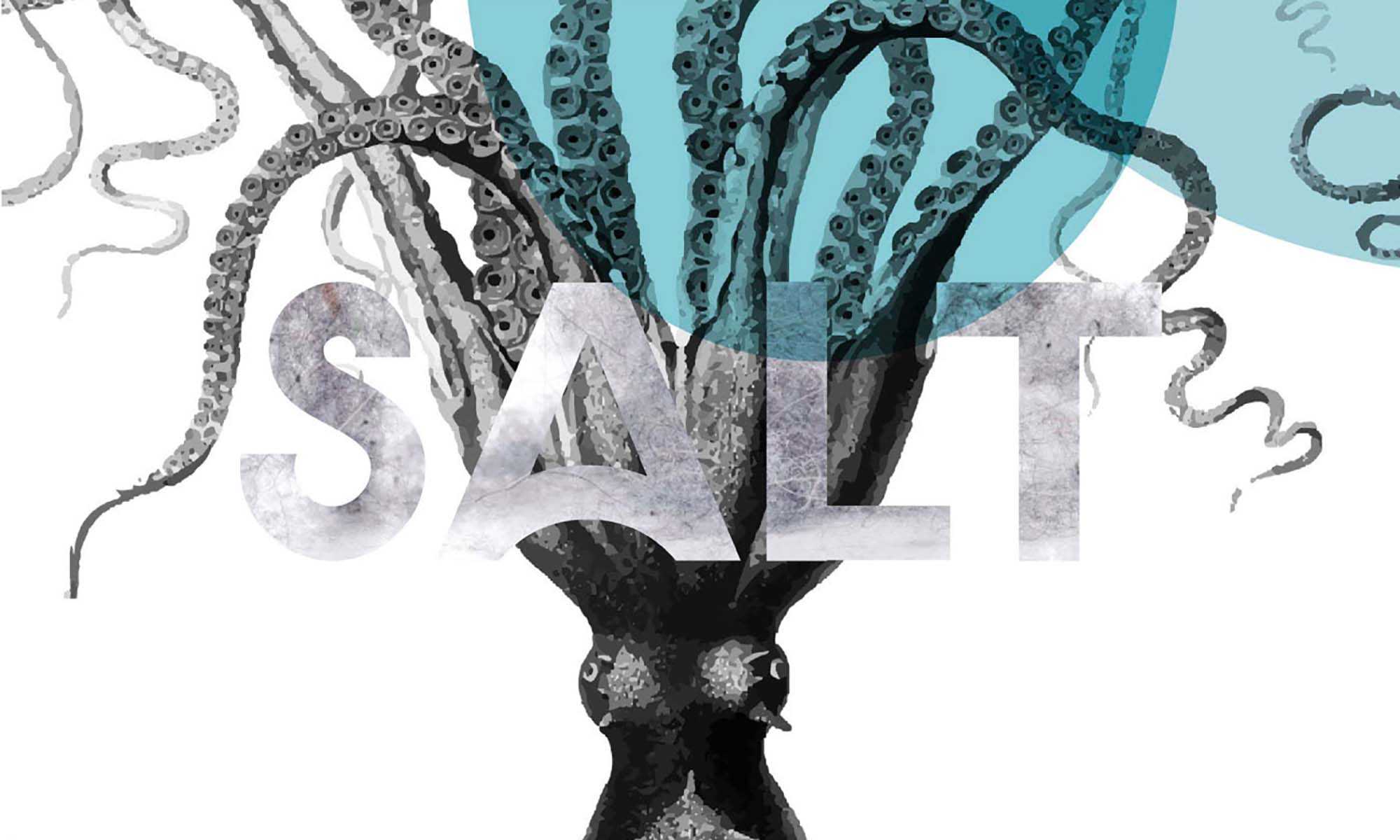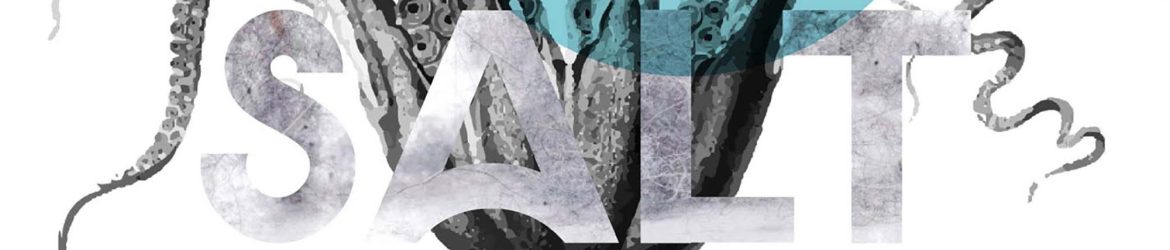
Salt Clean Minimalistic Sans Serif Font – Download Grátis
Salt é uma fonte sans serif meticulosa, que destaca suas curvas levemente curvadas e suas caudas, proporcionando uma experiência minimalista e limpa, uma verdadeira escolha ideal para quem valoriza um design moderno e sofisticado. Na categoria de mockups, a Salt Clean Minimalistic Sans Serif Font oferece uma aparência atraente e de alta qualidade, aperfeiçoada para se encaixar perfeitamente em qualquer projeto gráfico. É uma fonte que representa precisão e simplicidade, perfeitamente adaptada para criar uma aparência minimalista, sem perder a elegância e a sofisticação necessárias. Através da Salt Clean, você pode criar uma atmosfera elegante e minimalista em seus projetos, seja em uma página de site ou em qualquer outro tipo de layout gráfico.